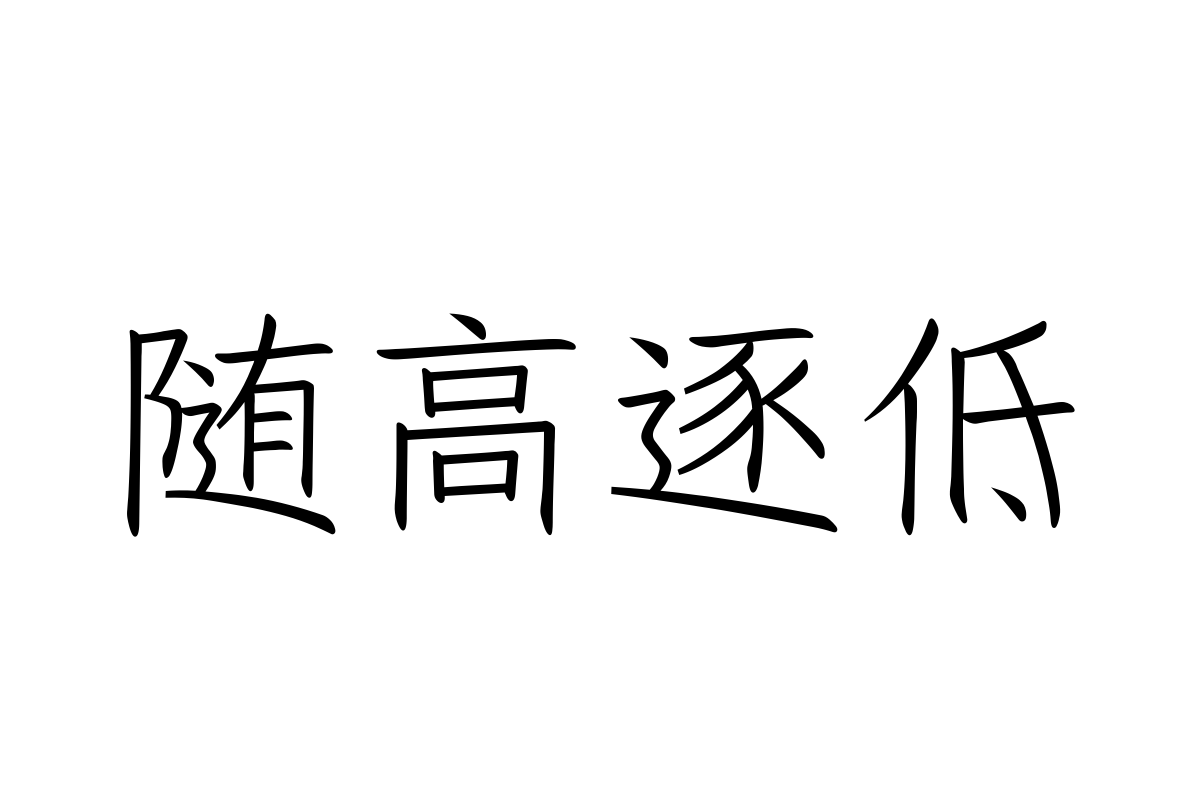
汉仪新枝体是一款由汉仪公司开发的中文字体,具有独特的设计风格和丰富的字形变化。这款字体采用了现代简约的设计理念,线条流畅、结构清晰,适合用于各种设计场景,如海报、宣传册、网页等。
汉仪新枝体的字形变化丰富多样,包括了多种不同的笔画和结构,可以满足不同设计师的需求。同时,这款字体还具有较好的可读性和辨识度,适用于各种印刷和电子媒体。
总的来说,汉仪新枝体是一款非常适合现代设计需求的中文字体,无论是在商业还是个人项目中,都可以作为一个重要的设计元素来使用。